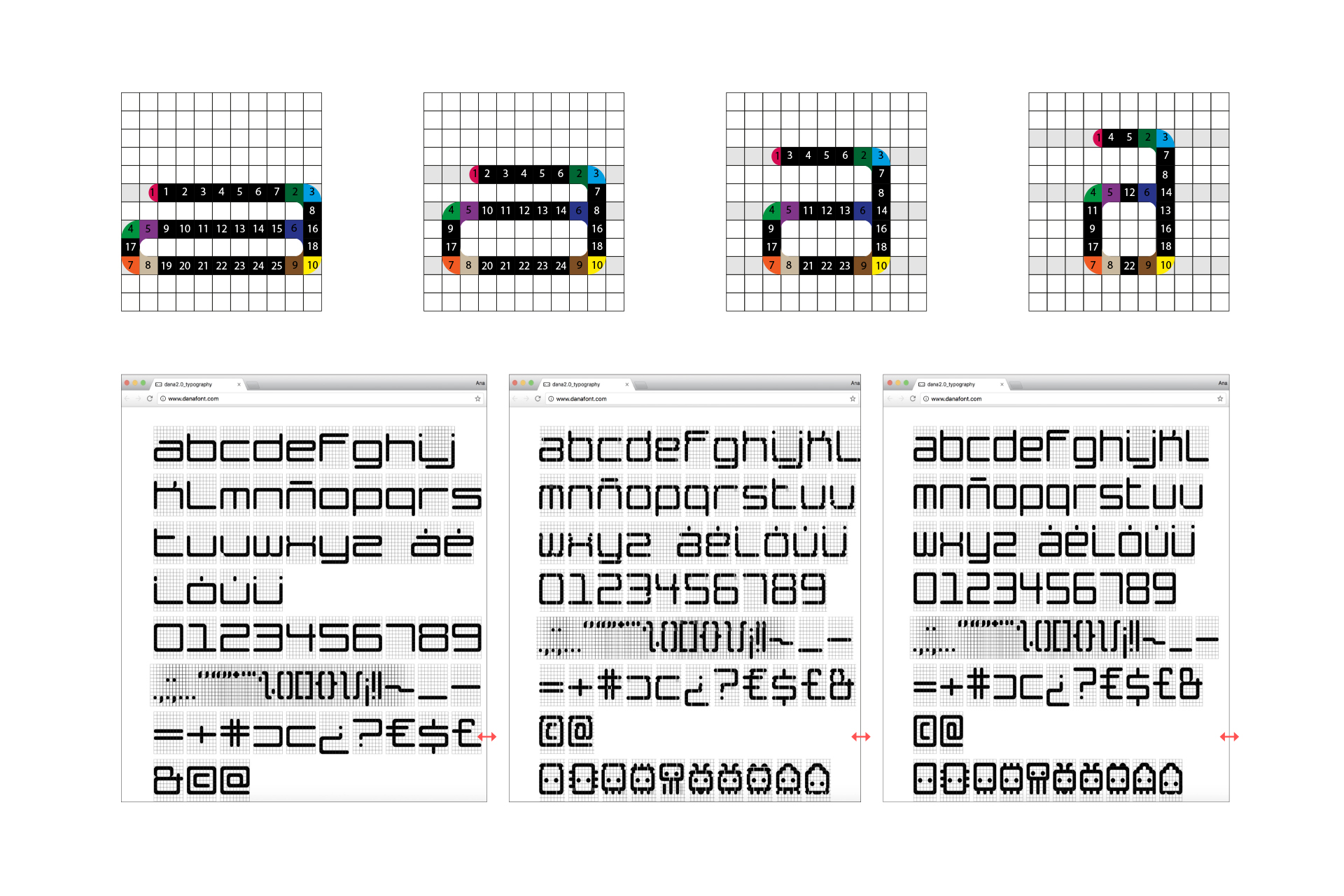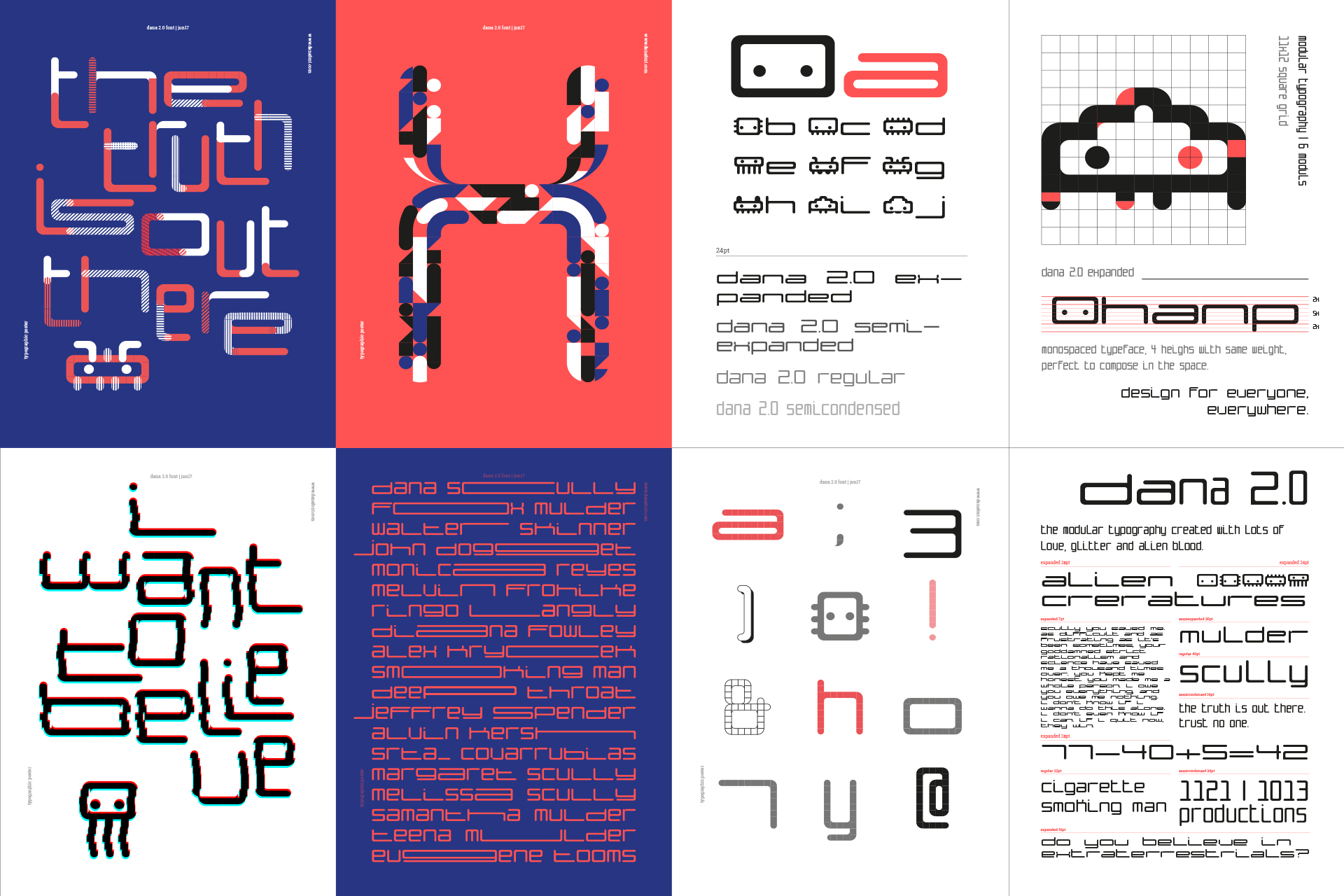
Ana Estrada, 2018
Danafont es una tipografía modular interactiva diseñada para entornos web. El sistema está construido con SVG, HTML, CSS y JavaScript, lo que permite que los glifos ajusten su morfología en tiempo real para adaptarse al ancho del navegador.
Su principal aportación es haber resuelto la necesidad de adaptabilidad tipográfica en la web mediante una solución de programación a medida. Es una aproximación pionera a la tipografía interactiva, desarrollada antes de que la tecnología de fuente variable se estandarizara. Esta innovación fue reconocida con un premio Laus de Oro en la categoría Digital en 2018.
La relevancia para esta investigación es que establece un precedente claro para los sistemas que posteriormente se desarrollan con fuentes variables. Es un ejemplo de cómo la necesidad de adaptabilidad en el diseño web impulsó soluciones técnicas específicas, incluso antes de que existieran estándares para ello.
- Década: Década de 2010
- Función: Accesibilidad
- Contexto: Investigación / Experimental
- Institución: Escuela Superior de Diseño de Madrid
- Grado de interactividad: Interacción débil o reactiva
- Input multimodal: No
- Tipo de input: Datos externos
- Tipo de output: Transformación morfológica
- Tecnología empleada: JavaScript, CSS
- Alfanumérica: Sí
- Mantiene codificación textual: No